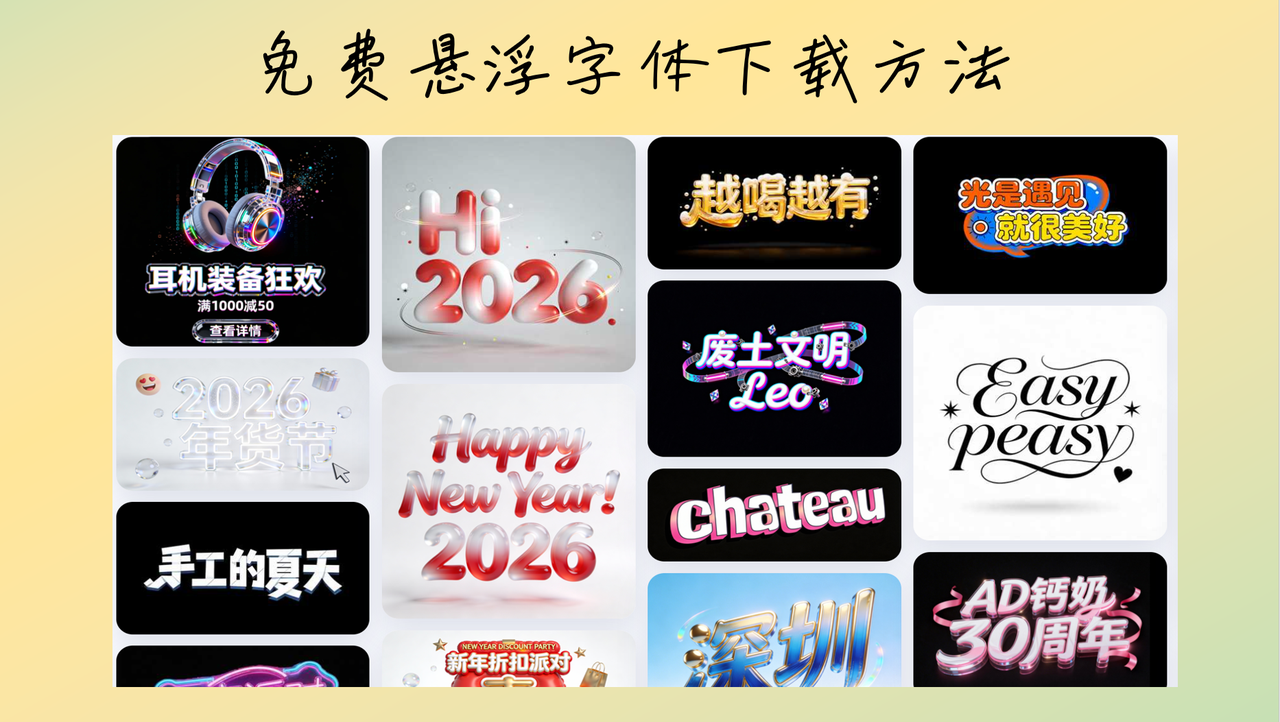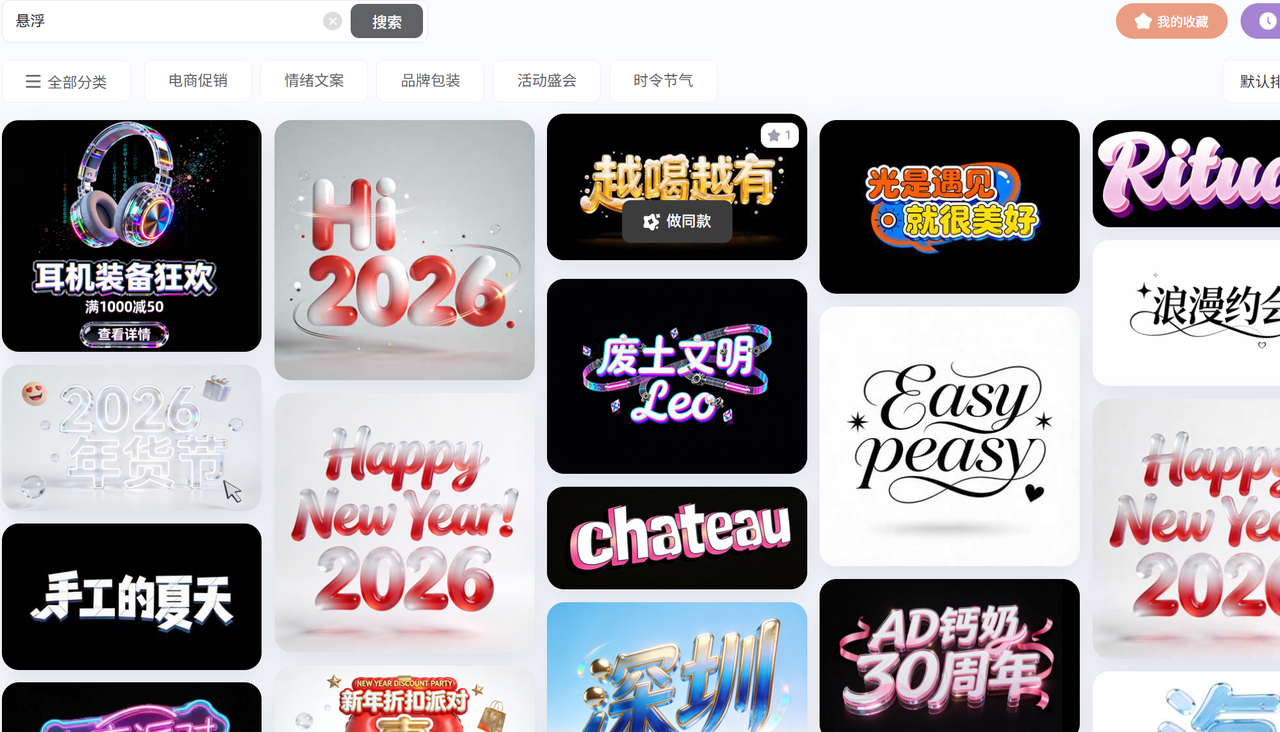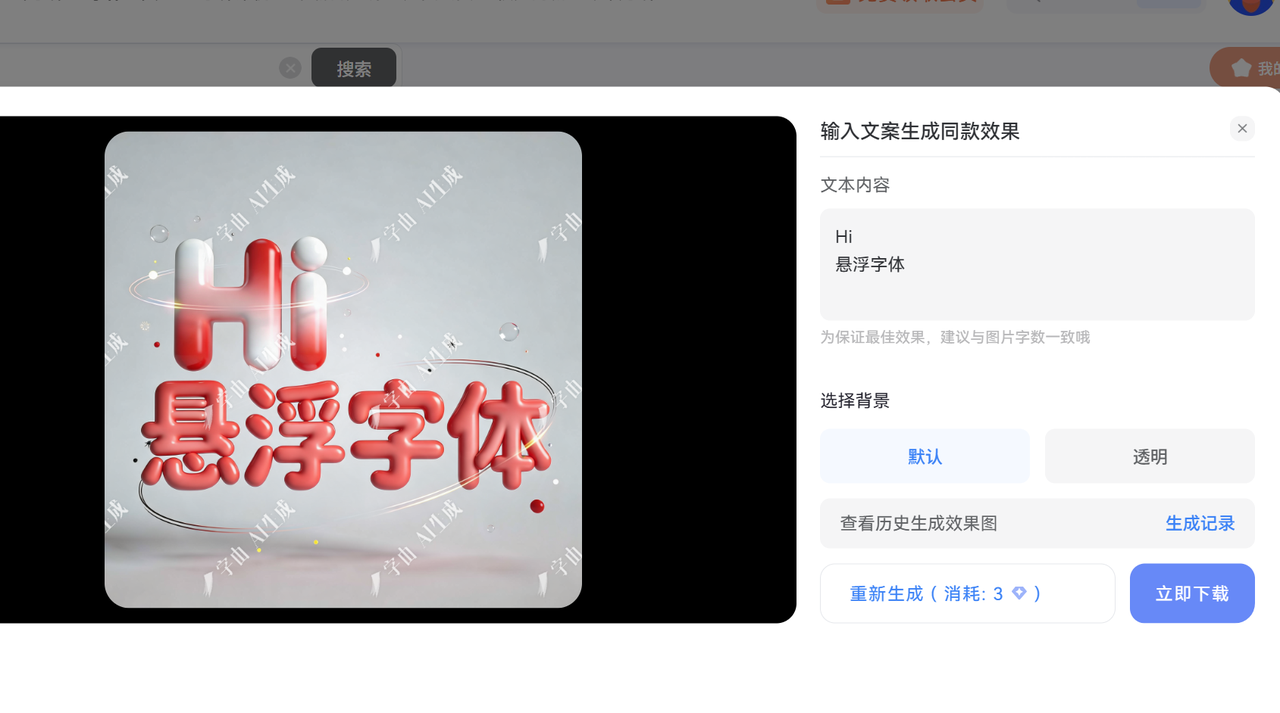
悬浮字体去哪下载?教你用 AI 生成悬浮字体
做设计这几年,我遇到过太多次这样的情况:花了几个小时做好海报,突然想起来字体可能有版权问题。尤其是悬浮字体这种视觉冲击力强的设计元素,删掉重做浪费时间,用免费字体又担心效果不够好。本文给大家推荐一个可以 AI 生成悬浮字体的方法,并且可以免费下载到本地。
AI生成字体介绍
字由AI字体是字由团队推出的一个在线字体生成工具。它最大的特点就是用AI技术来创建字体,你只需要查找自己想要的字体模板,输入想要的文字内容,系统就会自动生成对应的字体设计。
我第一次用的时候非常惊喜。更重要的是,生成的字体都是免费可商用的,不存在版权风险。
这个工具特别适合需要悬浮字体的场景。悬浮字体就是那种看起来有立体感、像漂浮在空中的字体效果,常用在海报、banner、品牌标题这些需要吸引眼球的地方。以前想要这种效果,要么自己在PS里一个字一个字做,要么买昂贵的商用字体。现在通过AI生成,省下了大把时间和预算。
悬浮字体生成
我把自己的实际操作步骤整理出来,跟着做一遍就能轻松下载到需要的字体。
第二步:在搜索框搜索“悬浮”
字体模板提供搜索功能,输入你的字体风格,比如“悬浮”,就可以获得所有悬浮字体的列表。
第三步:选择模板
第四步:生成悬浮字体
输入自己的文字,点击一键生成点击生成按钮后,等待大概30秒左右,就可以生成和模板同款的悬浮字体了。
AI生成悬浮字体的优势
速度快效率高
传统方式做一个悬浮字体效果,我需要在PS里调整图层样式、添加阴影、制作立体感,一个标题至少要花20分钟。如果客户要改风格,又得重新来一遍。
用AI生成的话,全程不超过5分钟。想要不同风格就重新选择模板,再生成,试错成本很低。遇到赶工期的项目,这个速度优势太明显了。
AI工具的出现让字体设计工作变得更简单,但这不意味着设计师的价值降低了。恰恰相反,当我们从繁琐的技术操作中解放出来,就能把更多精力放在创意构思和整体把控上。工具只是帮我们实现想法的手段,真正的设计判断和审美品味还是需要人来完成。